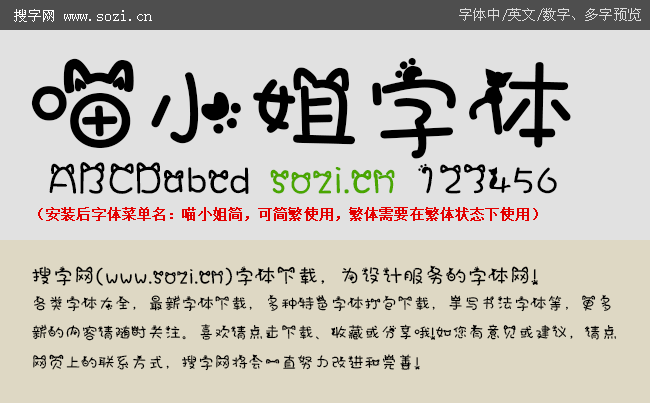
喵小姐字體
搜字網(wǎng)給大家提供一款喵小姐字體手機(jī)中文字體下載。這款手機(jī)字體是仿照兒童手寫風(fēng)格的卡通手寫字體,字體的部分筆畫變成了非?蓯鄣目ㄍ▓D案,是一款充滿童趣手寫風(fēng)格的卡通POP字體,特別適合喜歡手機(jī)字體個(gè)性一些的朋友在手機(jī)上安裝使用。